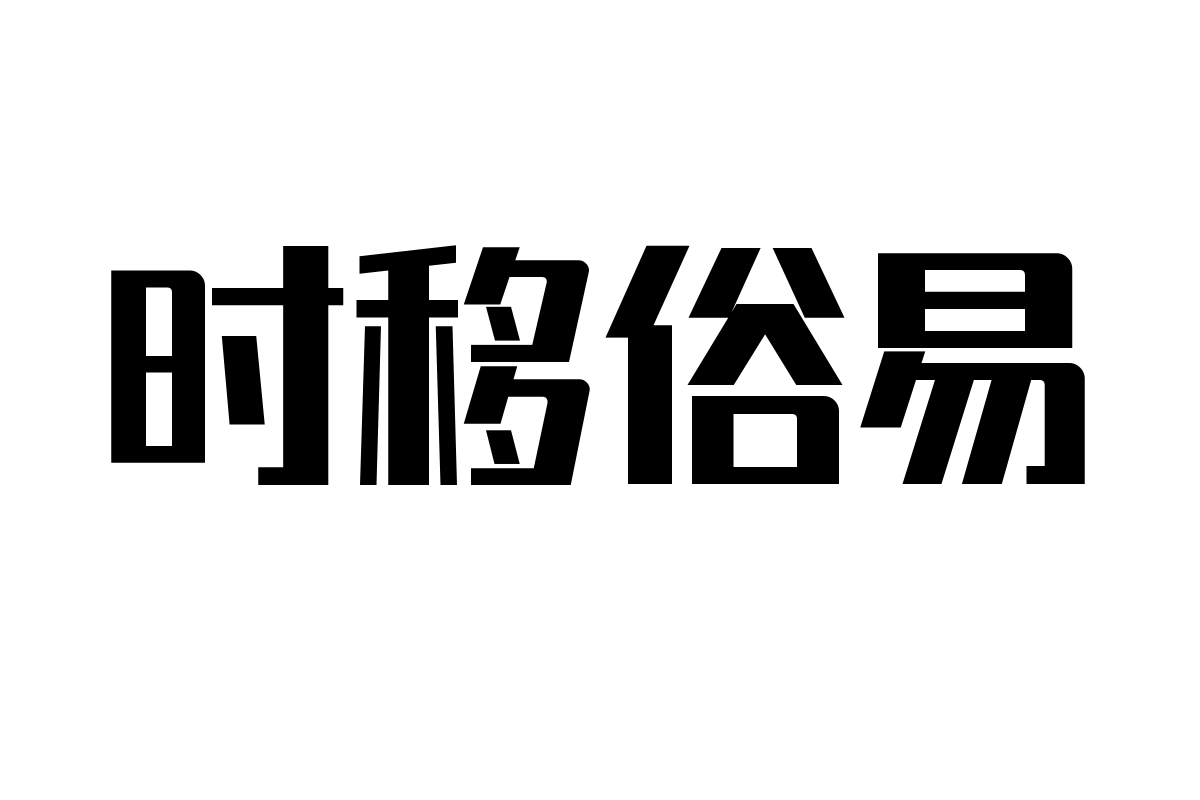
锐字潮牌真言大粗是一款具有独特设计感的字体,其特点是字形粗犷、有力,给人一种强烈的视觉冲击。这款字体适用于需要强调力量和动感的设计场景,如广告、海报、包装等。
锐字潮牌真言大粗的笔画粗细不一,既有粗壮的部分,也有细腻的部分,使得整个字体看起来既有力度又不失柔美。这种独特的设计使得它在众多字体中脱颖而出,成为了一种独特的风格。
此外,锐字潮牌真言大粗还具有一定的可塑性,可以根据设计师的需求进行一定程度的调整,以适应不同的设计需求。这使得这款字体在实际应用中具有很高的灵活性和适应性。
总的来说,锐字潮牌真言大粗是一款具有强烈视觉冲击力和个性特色的字体,适合用于需要强调力量和动感的设计场景。